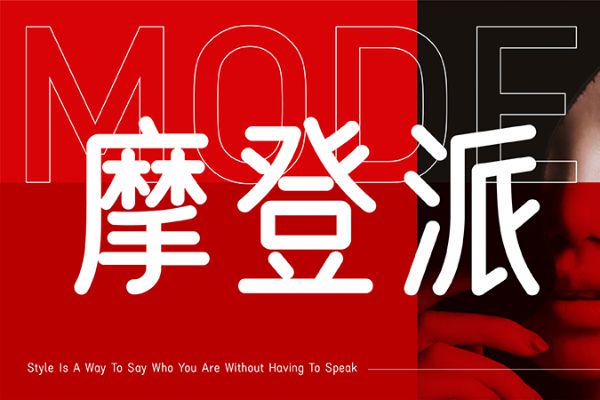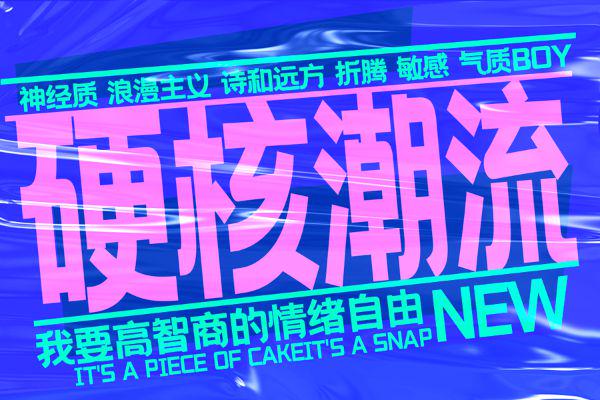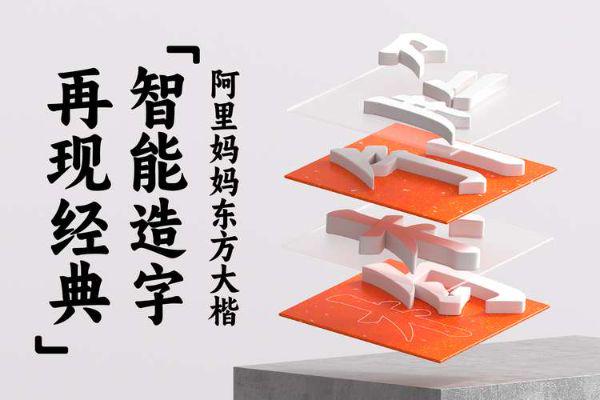
6款适合奶茶行业的字体推荐!助你打造特色品牌视觉
从门店招牌、产品包装,到菜单设计、宣传海报,在奶茶行业,一款合适的字体总能帮助品牌传递不同的风格特点。而不同奶茶品牌的定位不同,选择字体方案时也需要考虑不同类型的字体。比如主打清新风格的茶饮品牌,可以选择线条柔和、具有手写感的字体。而强调传统茶文化的品牌,则可以考虑带有书法气息或东方设计特点的字体。接下来,一起来看本文为你推荐的 6 款适合奶茶行业使用的字体吧,为你的奶茶品牌选择特色的字体风格。
1、优设好身体
优设好身体是一款整体风格偏向简洁、圆润和现代感的字体。它的字形结构比较清楚,笔画设计较为舒展,在视觉上具有自然亲切的感觉。奶茶品牌通常需要营造轻松、年轻的消费氛围,而它的字体特点能够很好地满足这一需求。在门店招牌设计中,这款字体能够保持较好的远距离识别效果;在菜单、新品海报和包装贴纸中,也能够呈现出简洁清爽的视觉效果。
并且优设好身体的适配性较强,可以与插画、水果元素、简约图形等设计元素结合使用,可以帮助你打造年轻化、自然感品牌形象。该款字体在【字由】站内也有提供,如果想要了解或使用的话,可以直接访问字由官网来查看。
2、字由文艺黑
字由文艺黑是在传统黑体基础上加入了一些设计变化,使整体视觉更加柔和,同时保留了较好的阅读体验。它不会像部分装饰性字体一样影响阅读,同时又能够让普通文字增加一定设计感。因此,它会适合用于奶茶店LOGO文字、产品名称以及宣传标语等场景。
3、阿里妈妈东方大楷
阿里妈妈东方大楷是一款具有传统书写风格的字体,整体呈现出较明显的手写特点。它的笔画变化丰富,能够为品牌设计增加文化气息和个性表达。
对于一些强调茶文化、东方美学或者特色产品系列的奶茶品牌来说,它能够帮助建立更加明确的视觉方向。例如在季节限定饮品、传统茶饮系列包装或者节日宣传设计中,东方大楷能够增强产品的主题感。
不过,这类风格明显的字体更适合作为标题或重点文字使用。如果应用范围过大,可能会降低信息阅读效率。
4、站酷小薇LOGO体
站酷小薇LOGO体是一款具有创意感的字体,字体造型更加灵活,适合用于品牌名称和视觉标题设计。奶茶行业面对年轻消费者群体,因此具有个性化特点的字体能够帮助品牌形成更鲜明的视觉印象。
这款字体适合应用在新品推广海报、活动页面以及社交媒体图片中。相比普通字体,它能够增加画面的设计感,让简单的文字内容更具表现力。
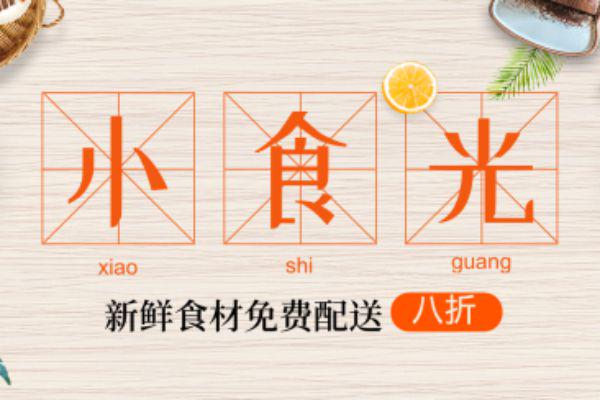
5、优设标题黑
优设标题黑是一款偏现代设计风格的字体,整体结构较为紧凑,视觉表现比较简洁有力。对于需要突出品牌名称、产品标题或者促销信息的奶茶设计场景来说,这类字体具有较好的展示效果。
奶茶店在制作新品推荐、菜单分类或者宣传活动海报时,通常需要让消费者快速获取关键信息。优设标题黑的字形特点能够帮助文字保持较高的辨识度,同时增加画面的层次感。
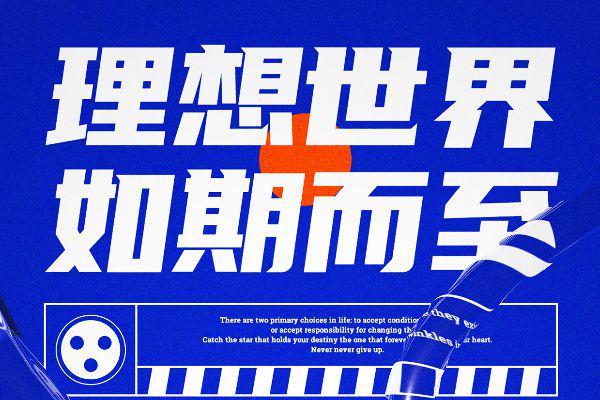
6、抖音美好体
抖音美好体是一款偏年轻化风格的中文字体,整体设计更加轻松自然,字形中带有一定的亲和感。对于奶茶行业来说,年轻消费者占据较大比例,因此具有活力和社交属性的字体更容易与品牌调性产生关联。
在实际设计过程中,抖音美好体适合应用于奶茶新品推广、活动海报、社交媒体宣传图以及包装贴纸等场景。它的字体风格不会过于正式,能够为设计画面增加轻松感。例如在制作季节限定饮品海报时,可以使用这款字体突出产品名称,让整体视觉更加符合年轻消费群体的审美习惯。